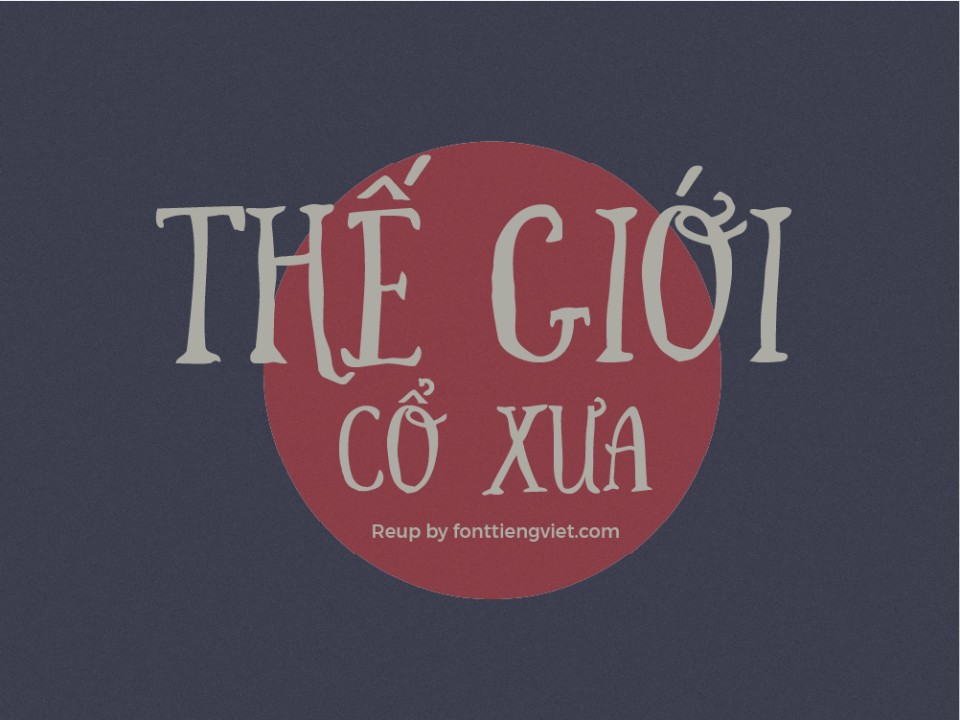
Font việt hóa iCiel Butcher and Block
Giới thiệu về Font việt hóa iCiel Butcher and Block
Trong thế giới thiết kế đồ họa, việc lựa chọn một Font Miễn Phí chất lượng luôn là ưu tiên hàng đầu của các bạn học sinh và giáo viên. Font việt hóa iCiel Butcher and Block là một bộ sưu tập độc đáo, mang đậm phong cách vintage và cổ điển của những thập niên trước. Được lấy cảm hứng từ những tấm biển quảng cáo thủ công và nhãn dán sản phẩm truyền thống, bộ font này mang lại cảm giác mộc mạc nhưng vô cùng mạnh mẽ. Việc iCiel thực hiện việt hóa giúp người dùng tại Việt Nam dễ dàng ứng dụng vào các dự án thiết kế tiếng Việt mà không lo lỗi dấu hay khoảng cách chữ.
Đặc điểm nổi bật của Font việt hóa iCiel Butcher and Block
Phong cách thiết kế đặc trưng
Bộ Font việt hóa iCiel Butcher and Block bao gồm hai phong cách chính là Butcher và Block. Trong khi bản Butcher mang những đường nét thô mộc, góc cạnh như những nét cắt thủ công, thì bản Block lại thể hiện sự vững chãi, vuông vức và đầy nam tính. Sự kết hợp này tạo nên một tổng thể hài hòa, giúp các bài thuyết trình hay báo tường của học sinh trở nên sinh động và có chiều sâu nghệ thuật hơn. Đặc biệt, font chữ này cực kỳ phù hợp cho các thiết kế poster học đường hoặc tiêu đề bài học cần sự nhấn mạnh.
Tính ứng dụng thực tế cao
Không chỉ giới hạn trong trang trí, font chữ này còn rất hữu ích cho các dự án in ấn áo lớp, làm logo hoặc thiết kế bìa sổ tay. Với độ tương phản tốt và dễ đọc, bộ chữ giúp thông điệp truyền tải một cách rõ ràng và ấn tượng nhất.